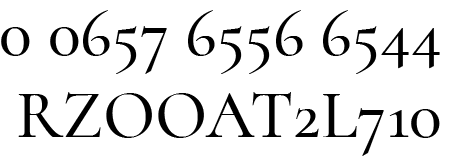
Cormorant Mediävalziffern ersetzen
Aber es geht um folgende Schrift: Cormorant… das Gesamtpaket beinhaltet leider nur Mediävalziffern, die für meine Anwendung sehr ungeeignet sind. Deshalb suche ich eine ähnliche (Google-Font) Schrift, die Versalziffern beinhaltet um die von der Cormorant zu ersetzen. Da es für ein Schulprojekt ist, sollen nur Google-Fonts verwendet werden…
Anbei Ein Beispiel der Mediävalziffern der Cormorant:
Die Cormorant beinhaltet auch Versalziffern, das lässt sich über die OpenType-Features steuern: